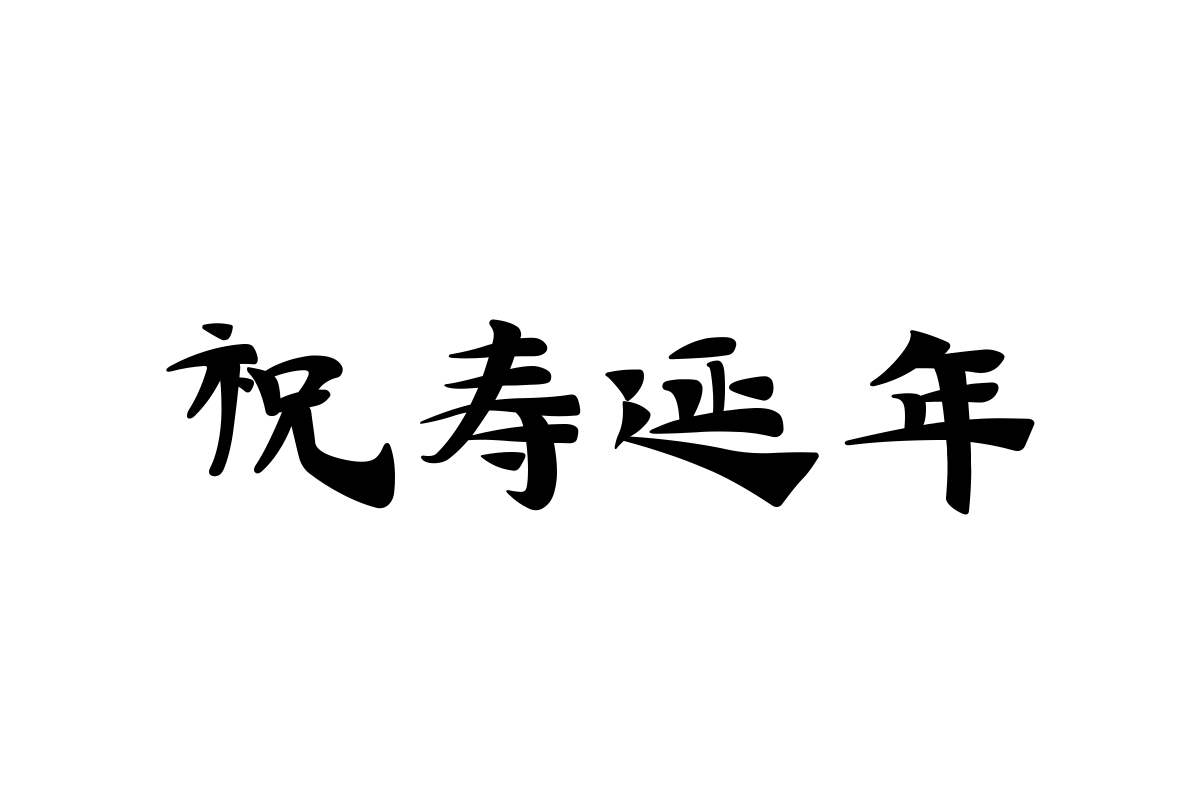
汉仪敦煌写经字体是一套具有浓郁中国古典气息的书法字体,其设计灵感来源于古代敦煌石窟中的经典佛教经文。这套字体以其独特的艺术风格和深厚的文化底蕴,受到了广大书法爱好者和设计师的青睐。
汉仪敦煌写经字体的特点主要体现在以下几个方面:
1. 字形结构:汉仪敦煌写经字体的字形结构严谨,笔画流畅,具有较强的视觉冲击力。每个字的笔画都经过精心设计,力求展现汉字的美感。同时,字体的大小、间距、行距等也经过精心调整,使整体布局更加和谐。
2. 笔触风格:汉仪敦煌写经字体的笔触风格独特,既有传统的韵味,又不失现代感。字体中的笔画粗细变化丰富,既有粗犷豪放的线条,又有细腻柔和的曲线,使得整个字体既有力量感,又不失灵动。
3. 装饰元素:汉仪敦煌写经字体在保持字形美观的同时,还融入了一些装饰元素,如波浪线、回旋纹等,这些元素既增加了字体的艺术性,又使其更加贴近敦煌文化的主题。
4. 兼容性:汉仪敦煌写经字体具有较高的兼容性,可以应用于各种场合,如网站、广告、书籍、杂志等。无论是用于正式的商务场合,还是用于休闲娱乐的场所,都能展现出其独特的魅力。
总之,汉仪敦煌写经字体是一款集传统与现代、东方与西方于一体的优秀字体,具有很高的艺术价值和文化内涵。